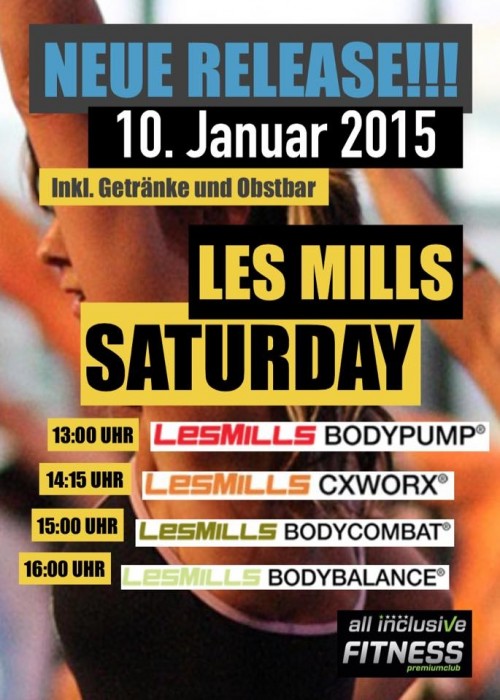
Suche schriftart (Fitness)
kann mir jmd. sagen mit welcher Schriftart die Texte erstellt worden sind? Mir gefällt diese Fette, recht gedrungende Schriftart.